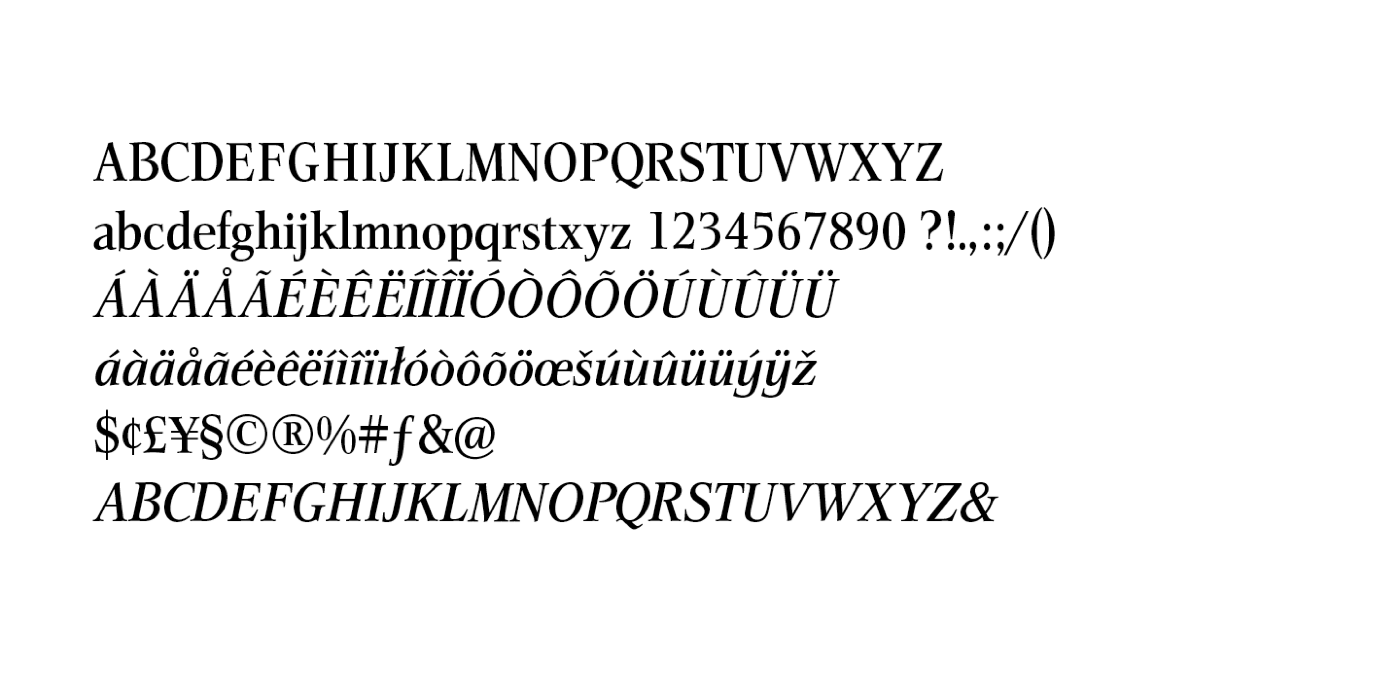
- 1989
- Antiqua humanistisch
Die Helicon ist eine Antiqua-Familie von David Quay aus dem Jahr 1989. Die Familie besteht aus vier Strichstärken mit Kursiven und einer westeuropäischen Belegung. Der Normalschnitt enthält auch Kapitälchen.